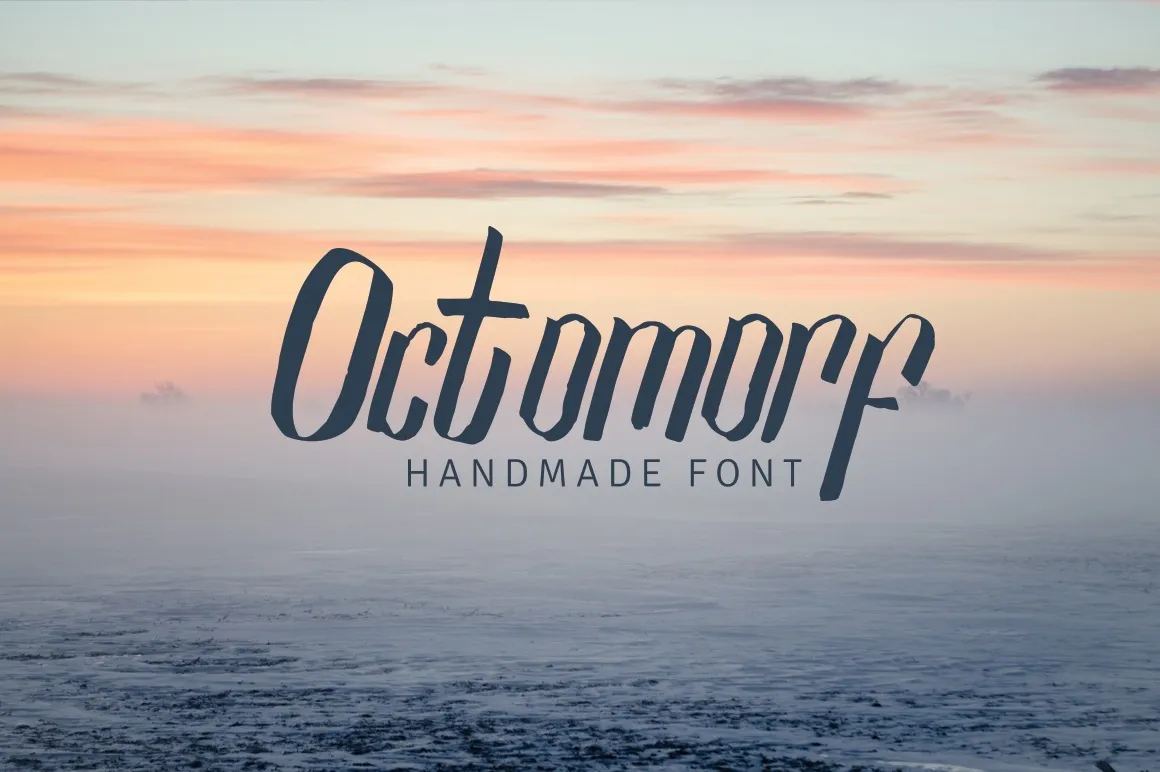
Octomorf Typeface – Fonte Grátis
Octomorf Typeface
Octomorf é uma tipografia cuidadosamente criada e projetada para atender a uma variedade de necessidades na comunicação visual. Com seu design natural e elegante, esta tipografia está disponível em duas versões, um tanto como uma mistura de forma geométrica com o realismo humano. Perfeita para os mais diversos projetos gráficos, Octomorf é perfeitamente adaptada para criações de logomarca, logos vintage, design de selo e até mesmo a adição de texturas em posters. O Octomorf também é adequado para criar um enfoque interessante na parte do texto ao lado das fotos que são usadas como uma base para frases typográficas criativas. Para finalizar o projeto, este design de fonte oferece suporte a diferentes idiomas e está preparado para ser usado nas capas de livros e embalagens de produtos. O Octomorf é mais do que apenas uma fonte: ele é um artifício gráfico versátil que pode se adaptar a qualquer tipo de projeto, tornando-o ideal tanto para os iniciantes quanto para profissionais da comunicação visual.